Fournier, Pierre Simon
Französischer Typograf, Stempelschneider und Schriftgießer. Geboren am 15. September 1712 in Paris. Gestorben am 8. Oktober 1768 ebenfalls in Paris. Pierre Simon (Pierre-Simon) Fournier gilt als der Schöpfer des »Point typografique« (Fournier Punkt) und der variablen, runden Drucknotentype für den Musiknotendruck.
In der Werkstatt seines Vaters Jean-Claude Fournier (o.A.–1729), der seit 1707 Geschäftsführer der renommierten Schriftgießerei der Familie Guillaume Le Bé (1525–1598) war, dem einstigen Kompagnon von Claude Garamond (um 1498/99–1561), erlernte Pierre Simon das Stempelschneiden, Stechen und Schriftengießen. Daneben wurde er von J.B.G. Colson im Zeichnen, in der Aquarellmalerei und im Holzschnitt unterrichtet. 1) Zu dieser soliden kunsthandwerklichen Ausbildung kam ein intensives Interesse an der Drucktechnik und der Entwicklung der Typografie, was Pierre Simon Fournier zu einem der frühesten Theoretiker und Historiker seiner Zunft machte.
Mit seiner »Table des proportions qu’il faut observer entre les caractères« veröffentlichte er 1737 die fundamentale Abhandlung über den »Point typografique« und das von ihm entwickelte typografische nichtmetrische Punkt-System, welches Firmin Didot (1764–1836) schließlich perfektionierte. 1739 wurde Fournier von der Pariser Syndikatskammer als selbständiger Schriftgießer registriert und konnte seine eigene, durchaus profitable Werkstatt errichten, nachdem sein älterer Bruder Jean-Pierre (1706–1783) bereits 1730 das väterliche Unternehmen übernommen hatte.
Fournier reformierte die traditionelle Renaissance-Antiqua, insbesondere durch die Angleichung der Oberlängen von Minuskeln von der k-Linie an die H-Linie der Majuskeln, und schuf in rascher Folge eine Vielzahl von Vorklassizistischen Antiquas, Schreibschriften und Ornamenten, sogenannten »Zierrat«, in zeitgenössischer Rokoko-Manier. Antiquas, wie beispielsweise die Fournier von Monotype, die Walbaum, die Meridien, die Linotype Centennial, die Versailles und die ITC Stone Serif basieren auf den Entwürfen von Fournier.
1742 erschien seine erste Sammlung von Schriftschnitten unter dem Titel »Modèles des caractères de l’imprimerie et des autres choses nécessaires au dit art«, die auch eine kurze Geschichte des Buchdrucks beinhaltete. Um die Mitte des 18. Jahrhunderts erfreute sich Fournier europaweiter Berühmtheit und war als Meister seines Metiers anerkannt: Schweden und Sardinien holten seinen Rat für den Aufbau königlicher Offizinen und Madame de Pompadour (Jeanne-Antoinette Poisson, dame Le Normant d’Étiolles, marquise de Pompadour, duchesse de Menars, 1721–1764), die illustre Maitresse König Ludwigs XV. (1710–1774), übertrug ihm die Einrichtung einer »Amateurpresse« in Versailles.
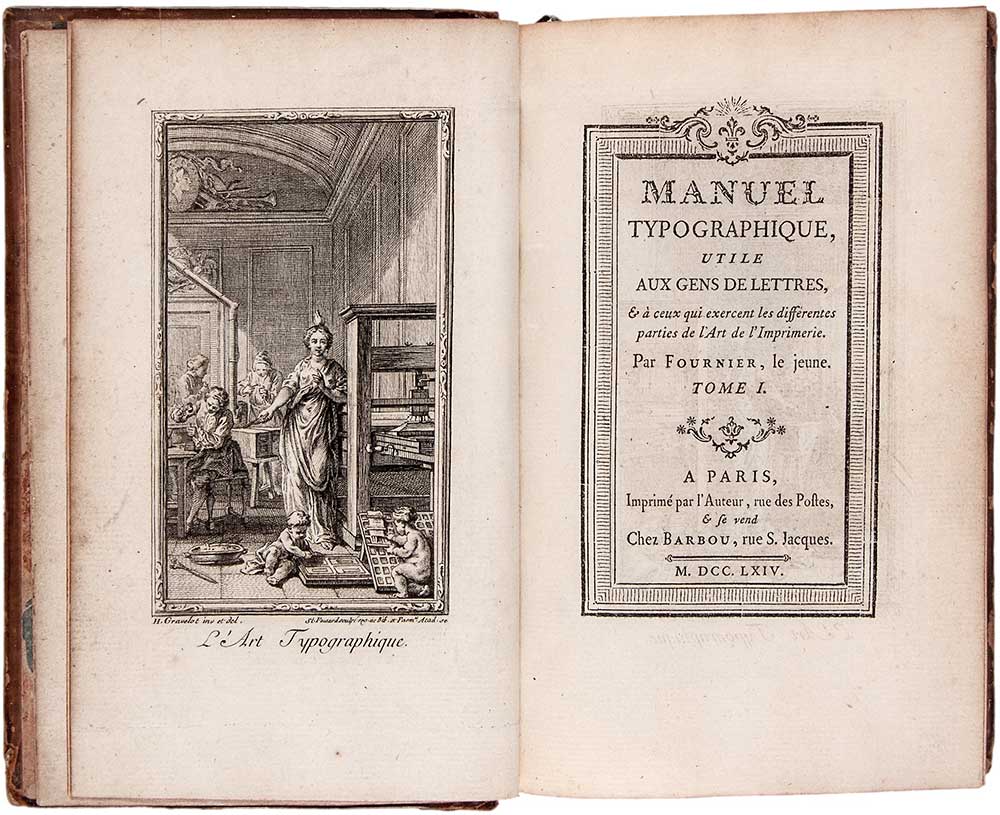
Fourniers theoretisches Hauptwerk ist das 1764–1766 publizierte Lehrbuch »Manuel typografique« über das neue Maßsystem. Daneben bezeugt eine lange Liste von diversen Veröffentlichungen unter anderem seinen eminenten Beitrag zur Entwicklung des Musiknotendrucks. Sein Wirken auf diesem Gebiet verlief im Zeichen einer heftigen Polemik gegen die Privilegien des berühmten Verlagshauses Le Roy & Ballard in Paris, dessen fast 200 Jahre altes, erbliches Monopol als Königliche Musikdrucker mit Hofbeamtenstatus jede Konkurrenz und damit jeden Fortschritt zu verhindern trachtete.
Die Familie Ballard hatte seit 1673 ein Patent inne, das selbst den Schnitt und Guss von neuen Notentypen ausdrücklich verbot. In einem jahrelangen, zermürbenden Rechtsstreit kämpfte Fournier vehement für die Durchsetzung seiner wesentlich vom Leipziger Verleger und Typografen Johannes Gottlob Immanuel Breitkopf (1719-1794) beeinflussten musiktypografischen Innovationen: Fourniers Typen imitierten in eleganter Weise die runde Form der geschriebenen oder gestochenen Note, waren voll flexibel, in allen Teilen (Notenkopf, -stiel, -fahne, Linienteilchen etc.) variabel und entsprachen damit besser der modernen musikalischen Schreibweise als die antiquierte, seit dem späten 16. Jahrhundert unverändert gebliebene rautenförmige Note der Ballards, die der Kompagnon Garamonds, Guillaume Le Bé (1525–1598), 1554 und 1559 für den Musikverleger Robert Ballard (um 1525/30–1588) entworfen und gegossen hatte.
1756 veröffentlichte Fournier seinen »Essai d’un nouveau caractère de fonte pour l’impression de la musique, inventé et exécuté dans toutes les parties typografiques« und 1760 vollendete er die Entwürfe für ein neues System des Musiknotendrucks, das 1762 auch patentiert wurde. Die Privilegien von Christophe-Jean-Francois Ballard wurden daraufhin zwar zeitlich auf die folgenden fünfzehn Jahre limitiert, eine legale Musikdrucklizenz der Pariser Syndikatskammer erhielt Fournier allerdings nicht. Zudem hatte auf Antrag seines ehemaligen Gießereilehrlings und nunmehrigen Konkurrenten Pierre-Francois Loiseau das Parlament in einem Erlass vom 24. Juli 1764 alle französischen Drucker ausdrücklich autorisiert, Musik zu drucken. Fournier resignierte, legte aber 1765 mit seinem »Traité historique et critique sur l’origine et les progrès des caractères de fonte pour l’impression de la musique, avec des épreuves de nouveaux caractères de musique, présentés aux imprimeurs de France« eine erste grundlegende Geschichte des Musikdrucks in Frankreich vor, die zugleich sehr eindrucksvoll seine fundierte Kompetenz bezeugte.
Pierre Simon Fournier starb am 8. Oktober 1768, im Alter von 56 Jahren, infolge von Strapazen und Erschöpfung, wie Zeitgenossen berichten. Nach seinem Ableben wurde die Pariser Gießerei bis 1775 von der Witwe Marie Madeleine Couret de Villeneuve (o.A.–1775), danach von seinem Sohn Simon Pierre Fournier le jeune (1757–o.A.) bis 1803 geführt. 2) 3) 4) 5)
| ↑1 | Quelle: Neues allgemeines Künstler-Lexicon oder Nachrichten von dem Leben und den Werken der Maler, Bildhauer (…), Verlag von E.A. Fleischmann, München 1837, Seite 427. |
| ↑2 | Literaturempfehlung: Nuñez, Pauline: Pierre-Simon Fournier, Typografe absolu, Typografe accompli?, Studienarbeit an der École Estienne DSAA Création Typografique Paris, 2007, online verfügbar unter http://luc.devroye.org/07_nunez_fournier.pdf (3.10.2016). |
| ↑3 | Literaturempfehlung: Neuedition des »Manuel typografique« in Französisch und Englisch in drei Bänden, dazu »Fournier on Typefounding«, an English translation of the text by Harry Carter in facsimile, with an Introduction and Notes by James Mosley, Darmstadt 1995. |
| ↑4 | Literaturempfehlung: Beaujon, Paul.: The XVIIIth century French typografy, Edition The Lanston Monotype Corporation, London 1926 bzw. in deutscher Sprache unter dem Titel: Pierre Simon Fournier und die Druckkunst des XVIII. Jahrhunderts in Frankreich, Berlin 1928. |
| ↑5 | Literatur von Pierre Simon Fournier: Table des proportions qu’il faut observer entre les caractères, Paris 1737. Modèles des caractères de l’imprimerie, Paris 1742. Essai d’un nouveau caractère de fonte pour l’impression de la musique, Paris 1756. Dissertation sur l’origine et les progrès de l’art de graver en bois, Paris 1758. De l’origine et des productions de l’imprimerie primitive en taille de bois, Paris 1759. Observations sur un ouvrage intitulé Vindiciae Typograficae, Paris 1760. Remarques sur un ouvrage intitulé Lettre sur l’origine de l’imprimerie, Paris 1761. Traité historique et critique sur l’origine et les progrès des caractères de fonte pour. l’impression de la musique, Bern 1765. Manuel typografique, utile aux gens de lettre et a ceux qui exercent les differentes parties de l’art de l’imprimerie, Paris 1764-66. Online verfügbar bei der Gallica, der digitalen Bibliothek der Nationalbibliothek von Frankreich, unter https://gallica.bnf.fr/ark:/12148/bpt6k1070584h (21.8.2025). |